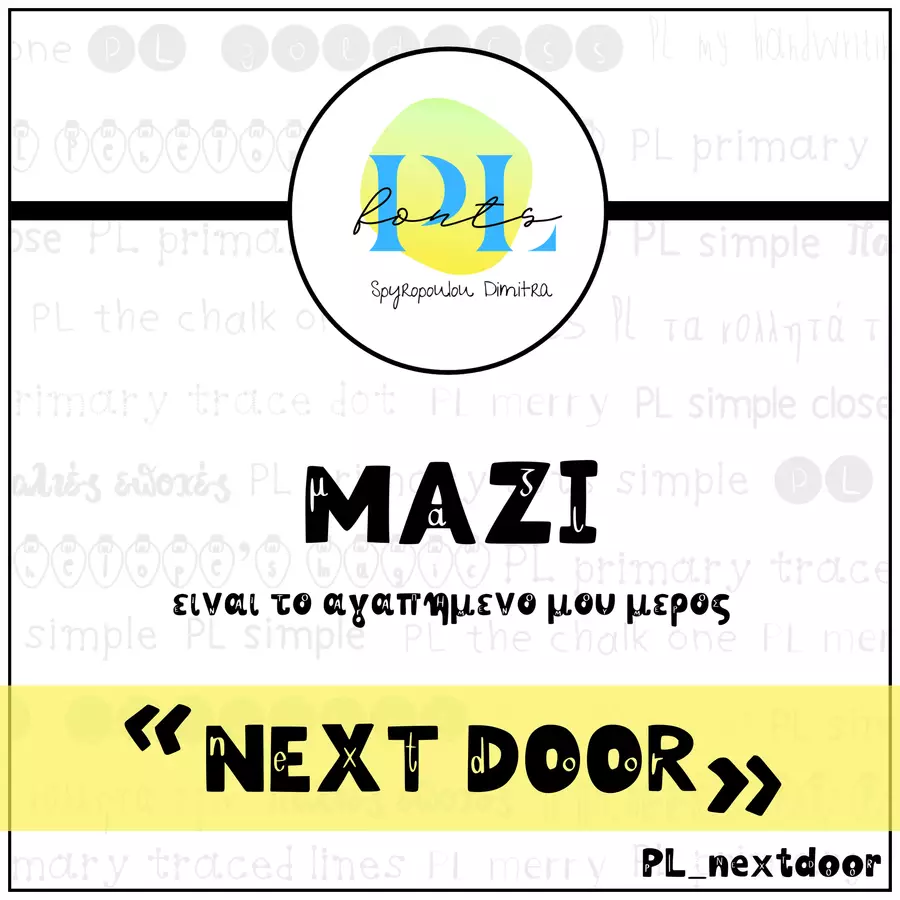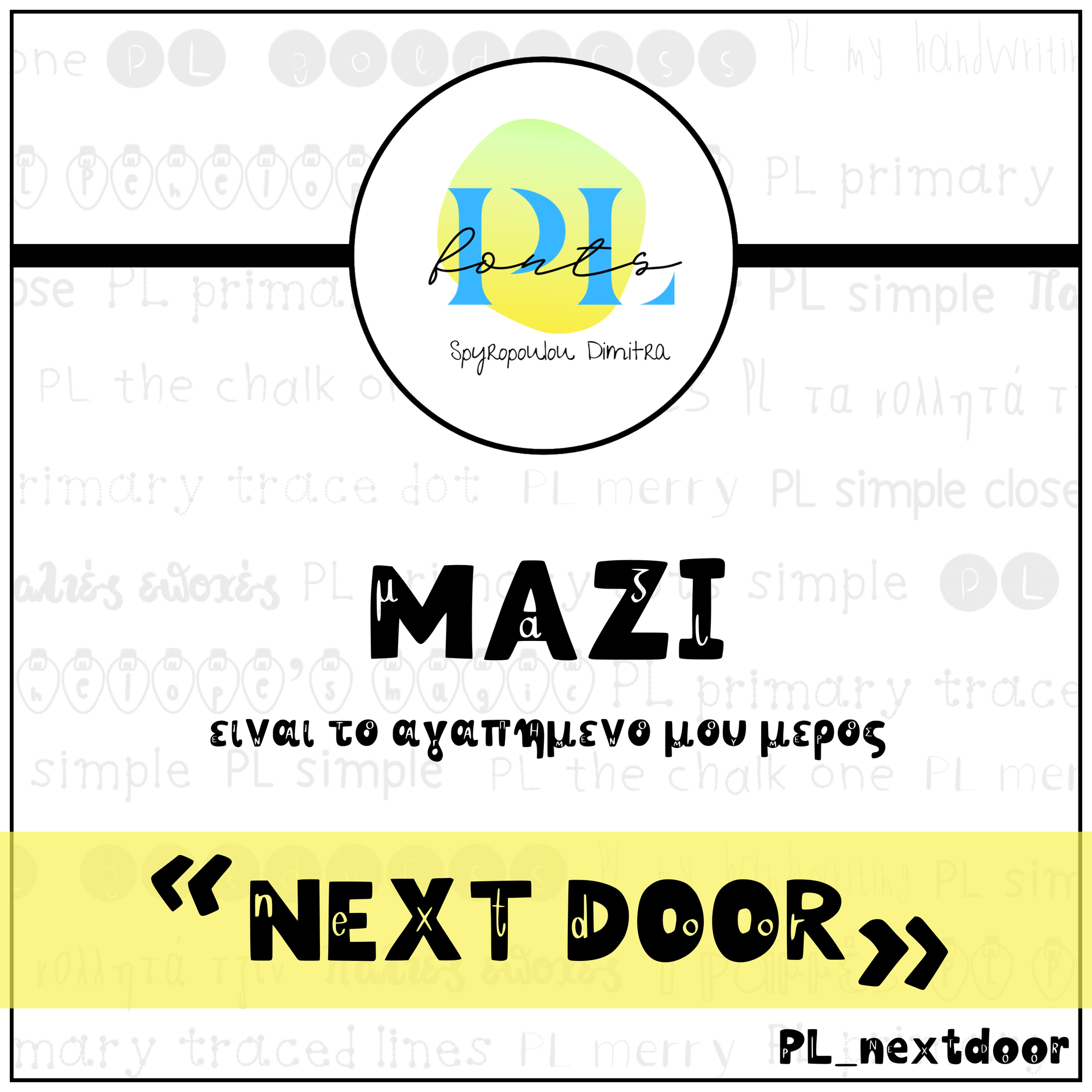
Μια νέα γραμματοσειρά η "Next door" με γράμματα κεφαλαία που μέσα τους αναγράφονται τα αντίστοιχα πεζά κι αντιστρόφως.
Όμορφη για διακόσμηση αρχείων, τίτλων, extra bold και εκπαιδευτική.